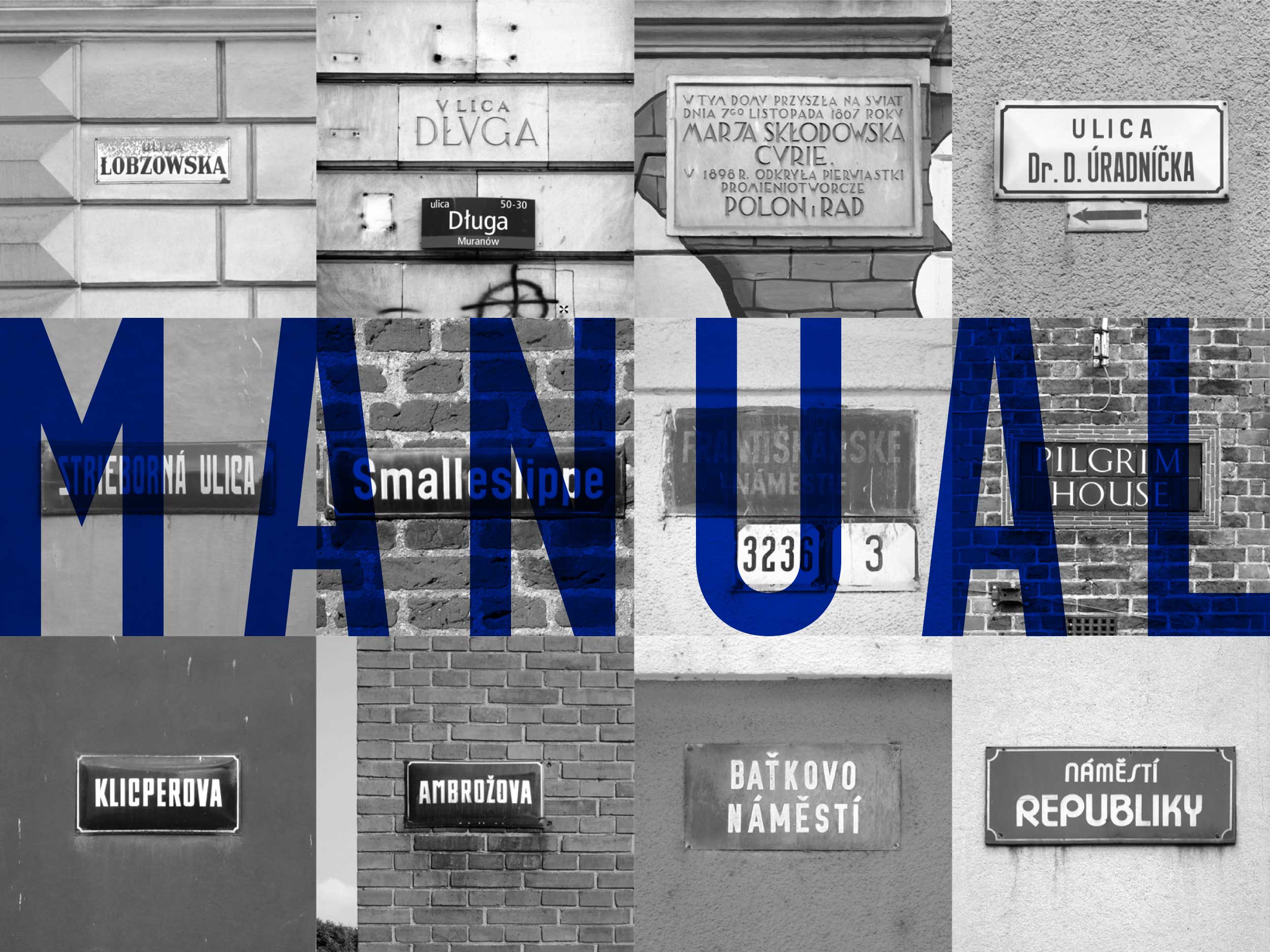
Manual Dizajn písmaCieľom projektu Manual je digitalizácia tradičných typov písma používaných v pred-digitálnej ére vo verejnom priestore na Slovensku, ich modernizácia a opätovné uvedenie do používania.
Type Atlas Online galériaType Atlas je účet na Instagrame publikujúci typografické nálezy z pred-digitálnej éry. Zameriava sa predovšetkým na nápisy, neóny, tesané nápisy a lettering z 20. storočia v Československu, ale často zaznamenáva nálezy aj zo starších období a iných krajín.
Fontstand AplikáciaFontstand je aplikácia pre operačné systémy macOS a Windows, ktorá umožňuje vyskúšať písma zadarmo alebo si ich prenajímať po mesiacoch na použitie na desktope aj webe za zlomok ich bežnej ceny.
Context of Diacritics WebstránkaContext of Diacritis je výskumný projekt a analýza frekvencie a kombinácií diakritických znakov vytvorená pre dizajnérov písma za účelom pomôcť s kompletizáciou znakovej sady.
Typable Webová aplikáciaTypable je jednoduchá webová aplikácia pre dizajnérov písma. Na rozdiel od bežných generátov textu, Typable umožňuje odstrániť alebo zmeniť znaky reálneho textu tak, aby ho bolo možné použiť na testovanie rozpracovaného písma.
Letters vs Math Online galériaLetters vs Math je Tumblr galéria so zaujímavými chybami znakov vznikajúcich pri interpolácii alebo automatizovaných modifikáciách.